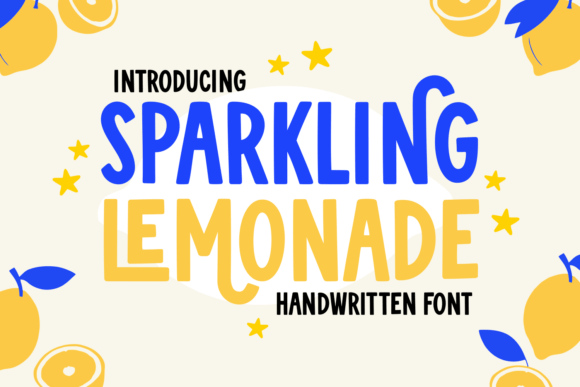
Sparkling Lemonade
Die richtigen Designelemente zu finden, kann eine Herausforderung sein, aber Sparkling Lemonade bietet eine außergewöhnliche Sammlung, die Ihre Arbeit sofort aufwertet.
Egal, ob Sie POD-Produkte (Print on Demand), Hochzeitseinladungen oder Social-Media-Grafiken erstellen, Sparkling Lemonade ist die ideale Wahl.